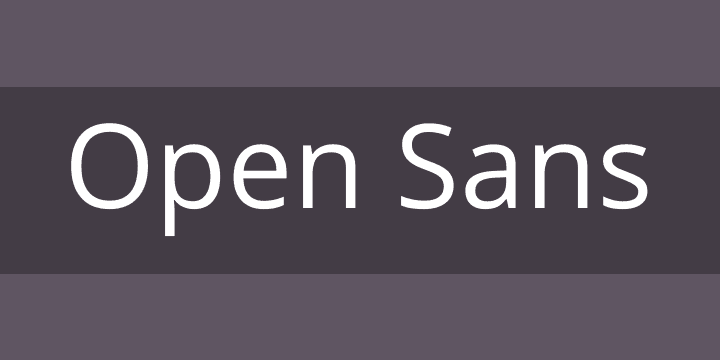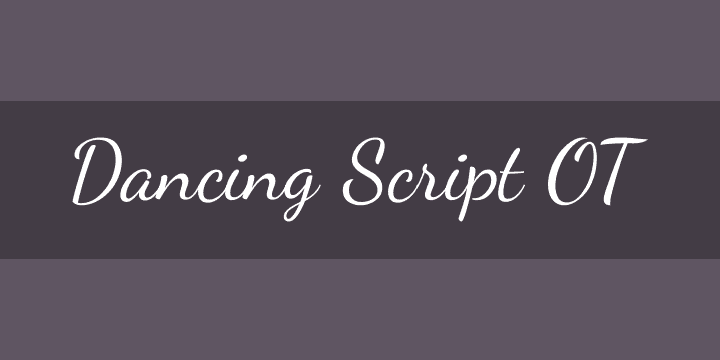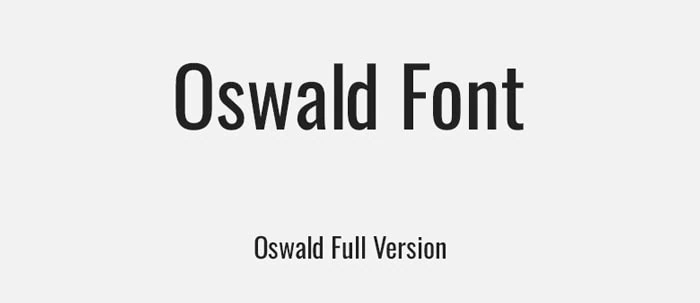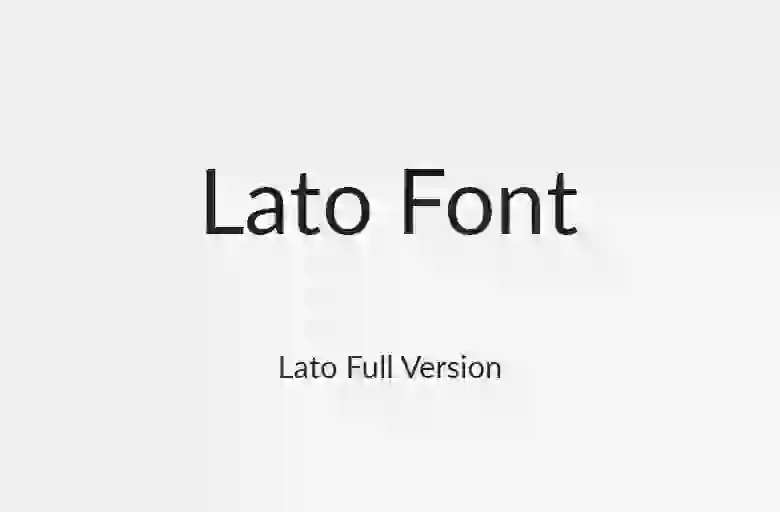
Font chữ PowerPoint tiếng Việt đẹp giúp bản thuyết trình chuyên nghiệp, tránh triệt để lỗi dấu và nhảy định dạng khi trình chiếu trên các thiết bị khác nhau. Việc ứng dụng đúng phông chữ không chỉ tăng thẩm mỹ mà còn giúp khán giả tiếp nhận thông tin hiệu quả hơn. Bài viết dưới đây hướng dẫn chi tiết danh sách phông chữ sắc nét và kỹ thuật nhúng font vào tệp tin cực nhanh chỉ mất vài phút thao tác.
Phân loại các nhóm font chữ PowerPoint tiếng Việt đẹp phổ biến
Để ứng dụng font chữ PowerPoint tiếng Việt đẹp một cách hiệu quả, bạn cần nắm vững đặc điểm kỹ thuật của 4 nhóm phông chữ cơ bản sau đây. Việc lựa chọn đúng nhóm phông chữ sẽ đảm bảo tính thẩm mỹ và sự đồng bộ cho toàn bộ bản thuyết trình.
Nhóm Sans-serif (Phông chữ không chân)
Đây là nhóm phông chữ hiện đại, tối giản với các đường nét có độ dày đồng nhất và không có gạch ngang ở các đầu chữ.
- Đặc điểm nổi bật: Khả năng hiển thị sắc nét tuyệt đối trên mọi loại màn hình điện tử và máy chiếu công nghiệp. Chữ không bị nhòe nét khi phóng lớn, giúp khán giả tiếp nhận thông tin cực nhanh.
- Ứng dụng hiệu quả: Lựa chọn ưu tiên cho phần nội dung chính (Body text) trong các bài báo cáo doanh nghiệp, tài liệu kỹ thuật hoặc slide công nghệ.
Nhóm Serif (Phông chữ có chân)
Nhóm phông này có các nét gạch nhỏ (chân chữ) ở đầu hoặc cuối các nét chính.
- Đặc điểm nổi bật: Mang lại cảm giác trang trọng, cổ điển và tạo độ tin cậy cao cho văn bản.
- Ứng dụng hiệu quả: Thường được sử dụng cho các bài thuyết trình về học thuật, lịch sử, văn học hoặc các tiêu đề cần sự trang nghiêm và đẳng cấp.
Nhóm Display (Phông chữ trang trí)
Bao gồm các phông chữ có kiểu dáng độc đáo, nét đậm nhạt rõ rệt hoặc được thiết kế cách điệu mạnh mẽ.
- Đặc điểm nổi bật: Tạo điểm nhấn thị giác và thu hút sự chú ý của khán giả ngay lập tức. Tuy nhiên, nhóm phông này gây mỏi mắt và khó đọc nếu trình bày các đoạn văn dài.
- Ứng dụng hiệu quả: Chỉ nên sử dụng cho Slide tiêu đề chính hoặc các câu trích dẫn ngắn để tạo hiệu ứng ấn tượng.
Nhóm Script (Phông chữ viết tay)
Mô phỏng nét bút ký hoặc chữ viết tay với các đường nối mềm mại và uyển chuyển.
- Đặc điểm nổi bật: Mang tính cá nhân, nghệ thuật và tạo sự gần gũi cho bài trình chiếu.
- Ứng dụng hiệu quả: Phù hợp cho các slide thiệp mời, lời cảm ơn hoặc các chủ đề sáng tạo cần thể hiện phong cách riêng độc đáo.
Danh sách 10 bộ font chữ PowerPoint tiếng Việt đẹp sắc nét
Dưới đây là tổng hợp các bộ font chữ PowerPoint tiếng Việt đẹp như Montserrat, Roboto, Be Vietnam Pro, Playfair Display, Lora… đã được Việt hóa và tối ưu hiển thị, giúp bản thiết kế của bạn luôn ổn định và thẩm mỹ.
Montserrat – Phông chữ hiện đại cho doanh nghiệp
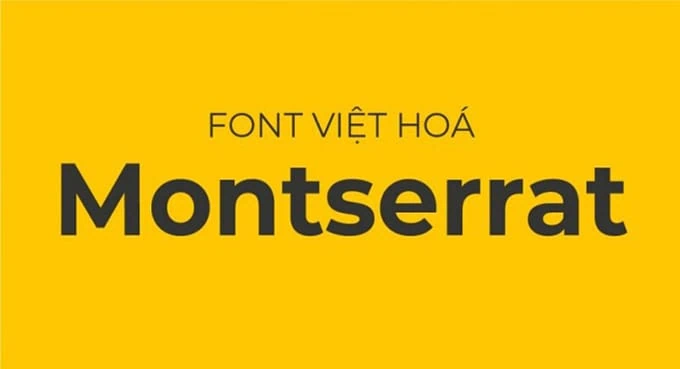
Montserrat được xem là lựa chọn phổ biến trong thiết kế slide hiện đại nhờ cấu trúc hình học cân đối và độ tròn trịa đặc trưng. Bộ phông này mang lại diện mạo sạch sẽ, tối giản nhưng vô cùng sang trọng, giúp không gian slide trông thoáng đạt và chuyên nghiệp hơn. Montserrat cung cấp nhiều độ dày khác nhau (từ Thin đến Black), cho phép bạn dễ dàng phân cấp thông tin giữa tiêu đề và nội dung. Đặc biệt, bản Việt hóa của Montserrat xử lý rất tốt các dấu thanh, giúp văn bản hiển thị sắc nét trên cả màn hình máy tính và máy chiếu hội trường.
Roboto – Sự lựa chọn cho bài thuyết trình công nghệ
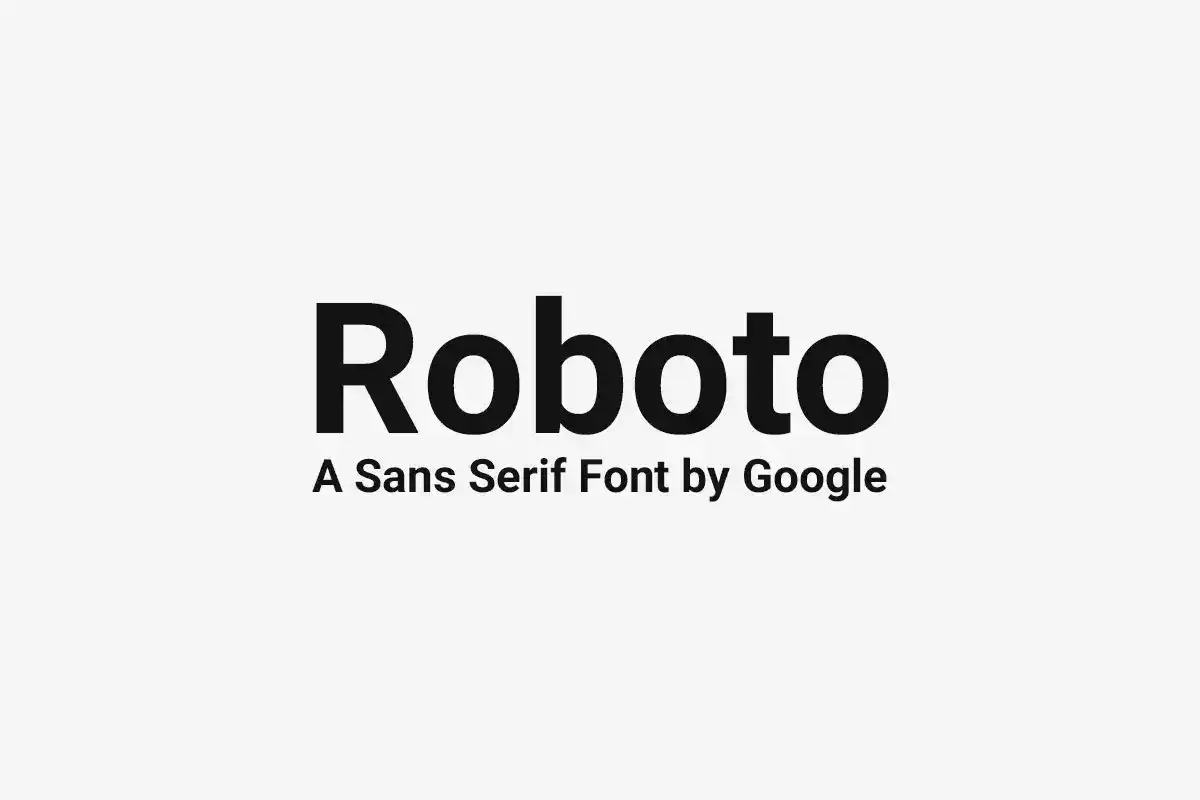
Được phát triển bởi Google, Roboto là sự kết hợp hoàn hảo giữa các đường nét kỹ thuật chắc chắn và những đường cong thân thiện. Đây là bộ font chữ PowerPoint tiếng Việt đẹp cực kỳ hiệu quả cho các chủ đề về phần mềm, kỹ thuật hoặc các báo cáo số liệu đòi hỏi sự minh bạch. Roboto có đặc tính dễ đọc (legibility) rất cao, giúp người xem không bị mỏi mắt khi theo dõi các slide chứa nhiều thông tin. Kỹ thuật thiết kế của Roboto cho phép các chữ cái được đặt sát nhau mà vẫn giữ được độ rõ ràng, giúp bạn tối ưu hóa không gian hiển thị cho các bảng biểu phức tạp.
Be Vietnam Pro – Tối ưu hoàn hảo cho tiếng Việt
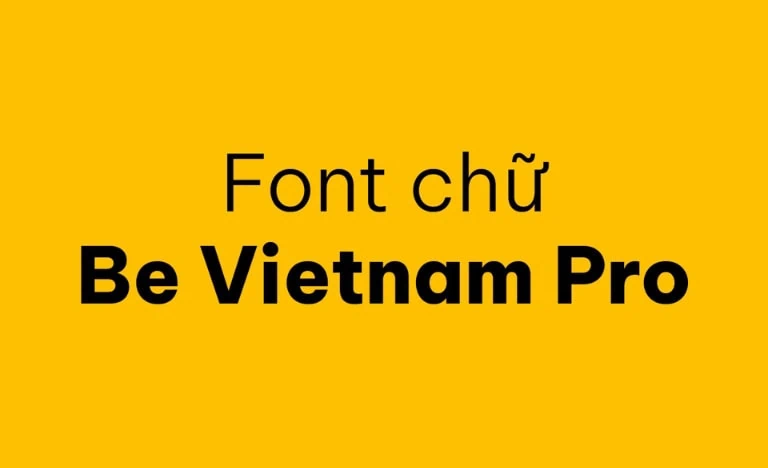
Be Vietnam Pro là bộ phông chữ hiếm hoi do chính đội ngũ kỹ sư người Việt thiết kế, vì vậy nó xử lý các dấu thanh (sắc, huyền, hỏi, ngã, nặng) một cách cực kỳ tinh tế. Hệ thống sẽ không bao giờ gặp tình trạng dấu quá cao làm chồng lấp lên dòng chữ phía trên hoặc bị lệch vị trí khi phóng lớn. Phông chữ này mang phong cách kỹ thuật nhưng vẫn có nét hiện đại, phù hợp cho cả tiêu đề lẫn nội dung chi tiết. Việc sử dụng Be Vietnam Pro giúp bản thuyết trình của bạn đạt độ đồng bộ tuyệt đối, thể hiện sự chỉn chu và am hiểu sâu sắc về phông chữ bản địa.
Playfair Display – Đẳng cấp cho phong cách thời trang
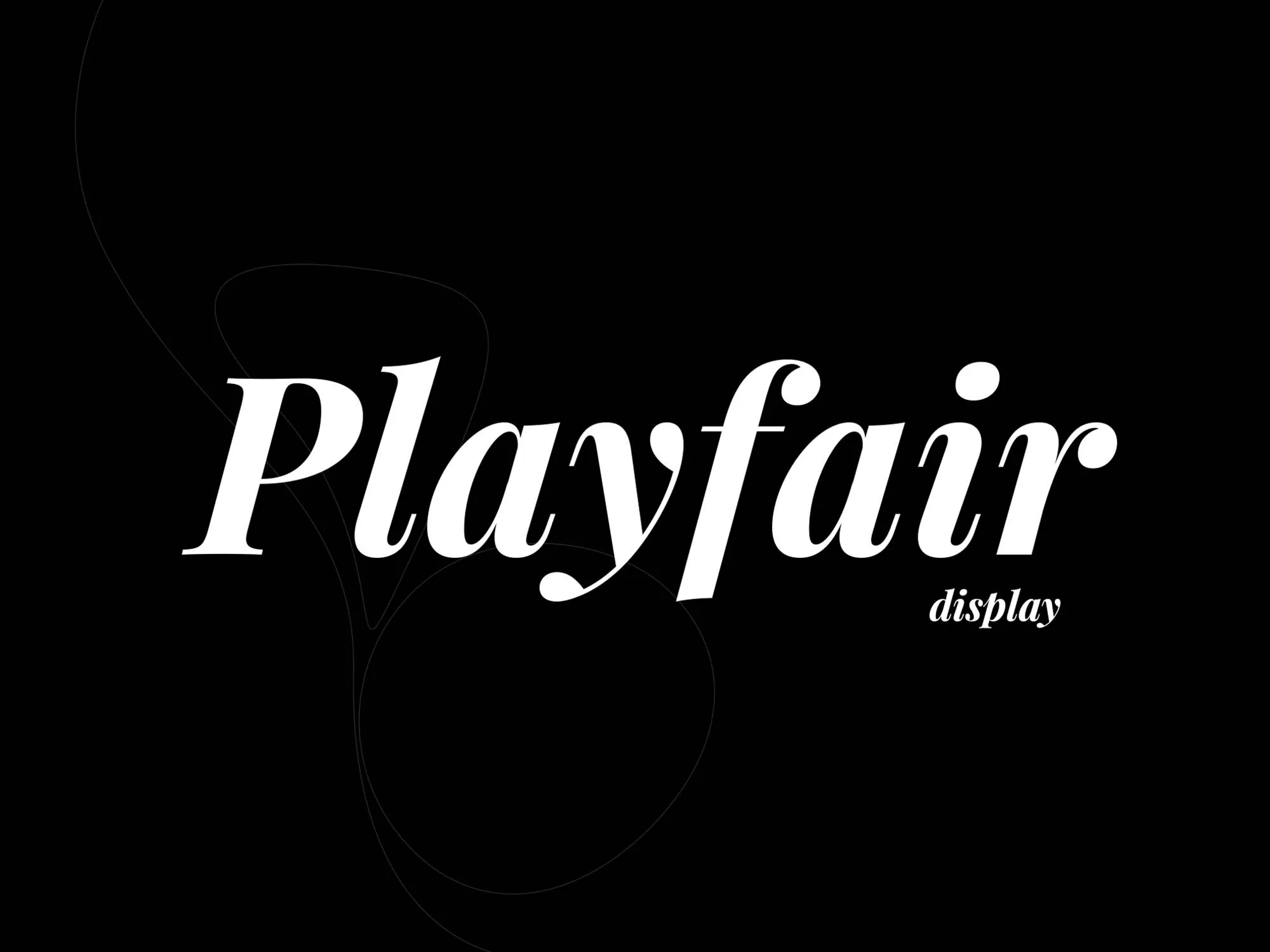
Nếu bài thuyết trình của bạn cần sự nghệ thuật, Playfair Display là giải pháp hiệu quả hàng đầu. Đây là phông chữ có chân (Serif) với sự tương phản mạnh mẽ giữa các nét thanh và nét đậm, mang lại cảm giác cổ điển nhưng vô cùng đẳng cấp. Playfair Display cực nhanh trong việc tạo điểm nhấn thị giác, vì vậy bạn nên sử dụng nó cho các slide tiêu đề hoặc các câu trích dẫn quan trọng trong ngành thời trang, nội thất hoặc kiến trúc. Để slide không bị rối, bạn hãy kết hợp phông này với một phông không chân đơn giản cho phần nội dung chi tiết.
Lora – Serif hiện đại và dễ chịu cho mắt